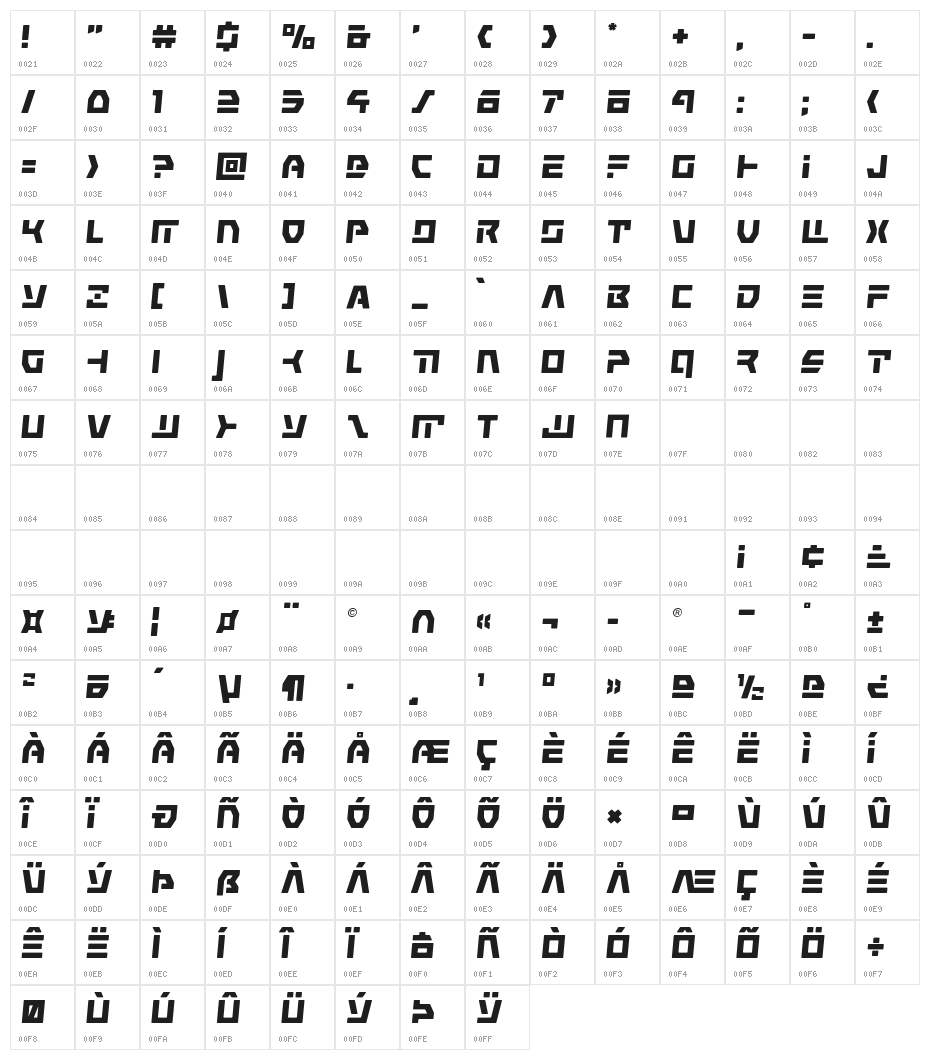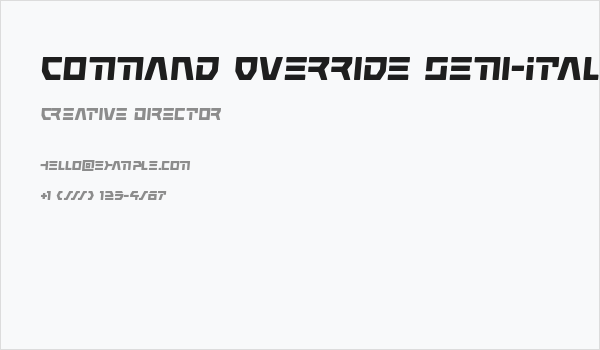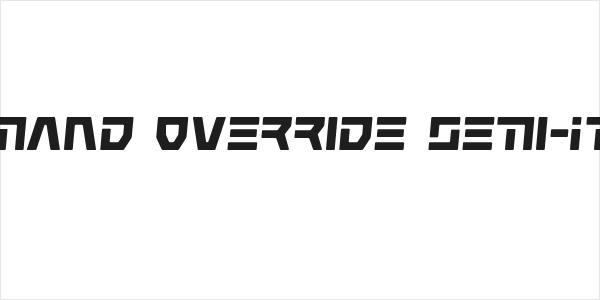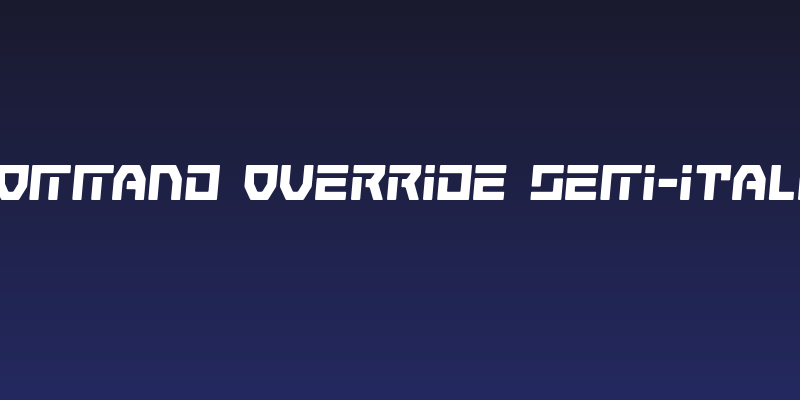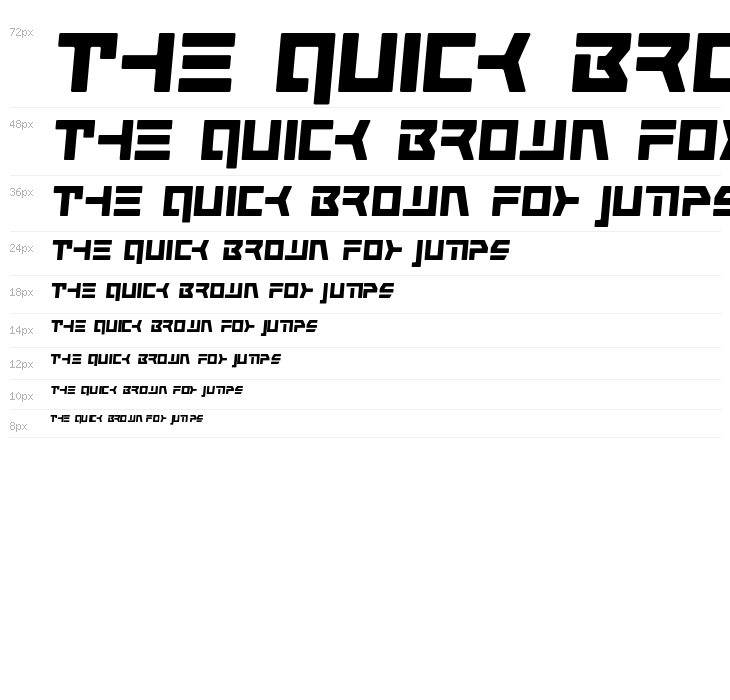
Command Override Semi-Italic Font
✎ Stencil
| Gesamtstil | Futuristic |
| Vorgeschlagene Projekte | Ideal for sci-fi themed projects, video game titles, tech branding, and futuristic posters. |